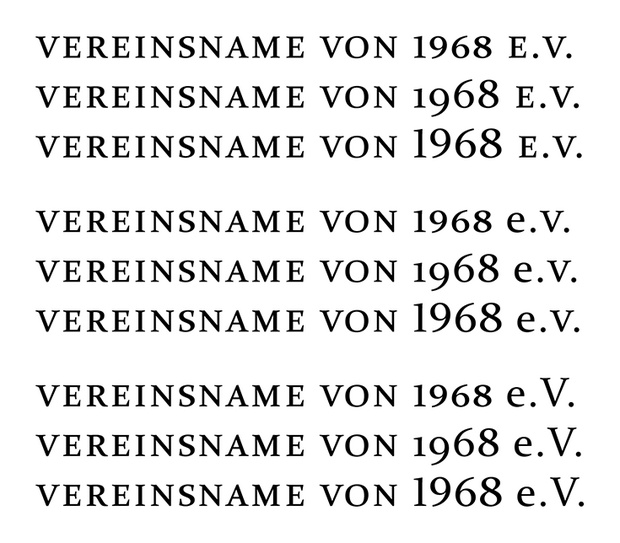
[Mitglied WASA…] Geschrieben März 17, 2012 Teilen Geschrieben März 17, 2012 Hallo liebes Forum! Mich würde wieder einmal Eure Meinung interessieren und Eure guten Ratschläge. Es geht um den Schriftzug eines Vereins, der in unterschiedlichen Anwendungen in einer Frakturschrift geschrieben wird. Bei einer anderen Anwendung bot es sich an, den Namen in "Kapitälchen" zu schreiben. Nun ist man sich aber leider nicht einig dort, ob das "e.V." mit Minuskel und Majuskel geschrieben wird oder beides sozusagen als "Kapitälchen"-Majuskel. Wo die noch gar nicht dran dachten, was aber auch ein Problem ist/sein könnte: Das Gründungsjahr ist ebenfalls im Vereinsnamen enthalten und wird in Schrifthöhe der Majuskel geschrieben (also: "Vereinsname von XXXX e.V.). Somit ist das Gründungsjahr optisch hervorgehoben. Die verwendete Schrift ist keine echte Schrift in "Kapitälchen", die nur aus "Kapitälchen" besteht. (Darf man das wirklich mittlerweile, nach Eurem Finden? Wenn nicht, gibt es für Standard-System-Schriften kostenlose echte Kapitälchenschriften?) Liebe Grüße Der WASA-Astronaut Edit und Anmerkung: Die Überlegung ist, ob ein "e.V." wie ein "TM" in dem Fall hochgestellt, © als Zeichen, GmbH, "€", etc. zu behandeln ist, oder als normale Buchstaben. Link zu diesem Kommentar
[Mitglied Diet…] Geschrieben März 18, 2012 Teilen Geschrieben März 18, 2012 Ich sehe in den meisten Fällen keinen rechten Sinn darin, Kapitälchen zu verwenden. Gut, manchmal ist es praktisch, diese zusätzliche Auszeichnung für eine spezielle Textsorte zu haben (z.B. Verfasserangaben in wissenschaftlichen Arbeiten). Aber ansonsten frage ich mich schon, wieso man Kapitälchen verwenden sollte, wenn man damit eine der wichtigsten Eigenschaften von Versalien, nämlich das gleichmäßige Schriftband, das durch das Fehlen von Ober- und Unterlängen entsteht, wieder zunichte macht. Link zu diesem Kommentar
[Mitglied Thie…] Geschrieben März 18, 2012 Teilen Geschrieben März 18, 2012 einfaches ausschlussverfahren: das einzige, was ich davon optisch erträglich finde, ist die oberste zeile. was meinen andere? bye thierry Link zu diesem Kommentar
[Mitglied Diet…] Geschrieben März 18, 2012 Teilen Geschrieben März 18, 2012 Ja. Link zu diesem Kommentar
[Mitglied WASA…] Geschrieben März 18, 2012 Themen-Ersteller Teilen Geschrieben März 18, 2012 Hallo und danke für Eure Antworten! Ich bin etwas spät dran heute... Bei der Sache, um die es geht, taucht der Vereinsname nicht an erster und wichtigster Stelle auf, aber schon im Titelbereich unter dem Titel. Trotzdem soll der Verein als Initiator hervorgehoben sein. Deshalb der Gedanke an die Kapitälchen. Alles in Großbuchstaben sieht mir zu "plump" aus. Ich finde die Kapitälchen da schon sehr passend. Mein Geschmack ist da vielleicht kein guter Maßstab. Aber dass die erste Version für Euch am besten ist, ist schon ein guter Hinweis. Wie geschrieben, es ging um die Befürchtung, dass man das "e" vielleicht immer klein schreiben sollte als typographische Regel. Es wird darauf hinaus laufen, dass ich den Bereich nochmal komplett überdenken werde. Eine andere Font kommt leider eher nicht in Frage, nur mit Bauchschmerzen. Schöne Grüße WASAAstronaut Link zu diesem Kommentar
[Mitglied Pach…] Geschrieben März 18, 2012 Teilen Geschrieben März 18, 2012 Nur noch mal zur Sicherheit: Reden wir hier von Fraktur-Kapitälchen? Deinen ersten Eintrag verstehe ich nämlich so. Fraktur-Kapitälchen sind aber genauso wie sonstiger Fraktur-Versalsatz ein fürchterliches typographisches Verbrechen, und da hat es wenig Sinn, über mikrotypographische Feinheiten nachzudenken. Link zu diesem Kommentar
[Mitglied Muec…] Geschrieben März 18, 2012 Teilen Geschrieben März 18, 2012 Apropos e.V.: http://de.wikipedia.org/wiki/EV schreibt Die Abkürzung e. V. (falsch ist e.V. ohne Leerzeichen) steht für:- eingetragener Verein (seltener: eV) siehe Verein Klingt zwar logisch, sehe ich aber gefühlt meistens ohne Leerzeichen ... Link zu diesem Kommentar
[Mitglied WASA…] Geschrieben März 19, 2012 Themen-Ersteller Teilen Geschrieben März 19, 2012 Hallo und danke! Hat sich doch gelohnt, nochmal nachzuschauen hier heute spät Abend. @Paschulke: Natürlich nicht! Es geht um "Standard-Schriftarten" bzw. Schriftarten internetkompatibel, die natürlich nicht Fraktur-Schriftarten sind. @Mueck: Da haben wir schon die nächste Stolperfalle! Mit Vereinen habe ich nicht so viel zu tun, und das, was man mal gelernt hat (auch im Hintergrund war), verblasst mit der Zeit. Also DANKE für den Tipp! Das wird abgespeichert und berücksichtigt, sofern es nicht sowieso vom Gefühl bedacht wurde (das weiß ich gerade nicht ganz sicher, aber relativ sicher, dass doch). Grüße WASAAstronaut Link zu diesem Kommentar
[Mitglied 4d28…] Geschrieben März 19, 2012 Teilen Geschrieben März 19, 2012 … sehe ich aber gefühlt meistens ohne Leerzeichen ... Richtig gesetzt wird es meist mit einem schmalen Leerzeichen, da der Leerraum dann optisch stimmt. Link zu diesem Kommentar
[Mitglied Seba…] Geschrieben März 19, 2012 Teilen Geschrieben März 19, 2012 Wobei die Kombination ".V" ja in den seltensten Fällen ein Kerning hat ... somit ergibt sich der (halbe) Leerraum meist auch schon ohne aktives Zutun von diesem ... Wäre ein perfektes Lehrbeispiel für den "Typokurs – drittes Semester: Ihr kennt jetzt die Regeln und findet sie toll – nun schaltet bitte das Hirn wieder ein und vertraut eurem Auge." Link zu diesem Kommentar
[Mitglied Josh…] Geschrieben März 19, 2012 Teilen Geschrieben März 19, 2012 Wenn die Schrift keine Kapitälchen enthält, sind die Kapitälchen einfach verkleinerte Großbuchstaben. Die sollte man zusammen mit normalen Großbuchstaben nicht verwenden. Wenn Du eine ganze Zeile in falschen Kapitälchen setzt, kannst Du auch gleich die Großbuchstaben in der gewünschten Größe benutzen. Um welche Schrift handelt es sich? Von der Times gibt es eine kostenlose Fassung mit Kapitälchen namens Doulos: http://scripts.sil.org/cms/scripts/page.php?site_id=nrsi&id=DoulosSIL_download#7de9e023 Auch ich würde „e. V.“ insgesamt aus Kapitälchen setzen, wenn sonst alles aus Kapitälchen gesetzt ist. Link zu diesem Kommentar
[Mitglied Thie…] Geschrieben März 19, 2012 Teilen Geschrieben März 19, 2012 die in dem beispiel oben von mir verwendete schriftart ist übrigens die kostenlos verfügbare constantia. diese und die anderen cleartype-schriftarten haben alle ›echte‹ kapitälchen, an die du in word 2010 oder professioneller layout-software rankommen müsstest. Link zu diesem Kommentar